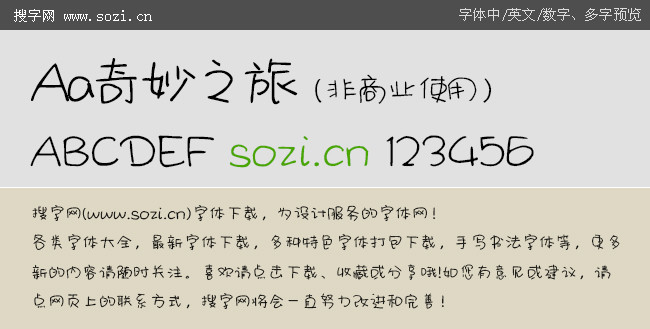
Aa奇妙之旅
搜字網(wǎng)給大家提供一款A(yù)a奇妙之旅(非商業(yè)使用)中文字體下載,該字體是一款非常個性的藝術(shù)字體,字體形狀充滿變化,帶有濃濃的卡通風(fēng)格,趣味性十足。適用于平面宣傳設(shè)計、網(wǎng)頁設(shè)計、海報設(shè)計等應(yīng)用(此字體為個人非商用版,商用可以聯(lián)系QQ:1006760504)。